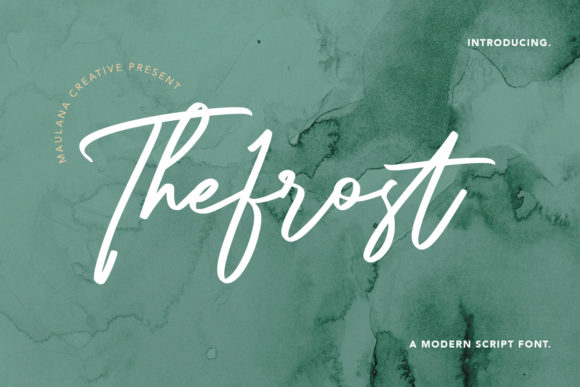
The Frost Modern Script
Trovare i giusti elementi di design può essere difficile, ma The Frost Modern Script offre una collezione eccezionale che eleva istantaneamente il tuo lavoro.
Realizzato con precisione, The Frost Modern Script fornisce vettori puliti, tipografia fluida e una licenza commerciale per la massima tranquillità.